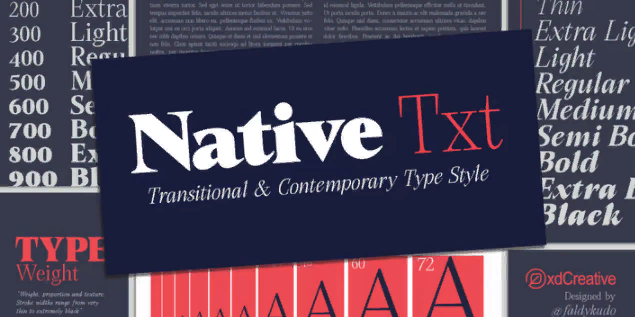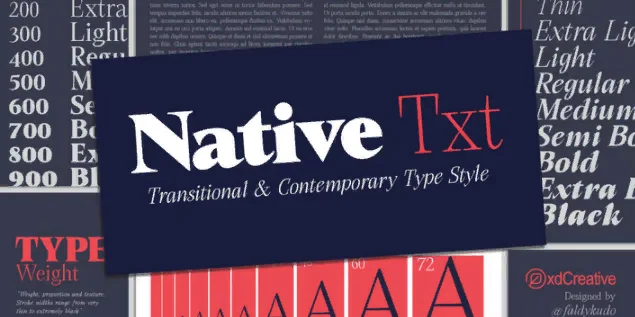
Название: Native Txt Font (2021)
Он сочетает в себе переходный и современный стили, с переменным углом наклона и большим контрастом начертания.
Native-txt имеет различные стили, но большинство из них имеют большую высоту x-height со скобками, засечками и квадратными терминалами, а также небольшую
открытая диафрагма.
Native-Txt предлагает настоящий курсив с каллиграфическим латинским стилем, очень контрастный и элегантный.